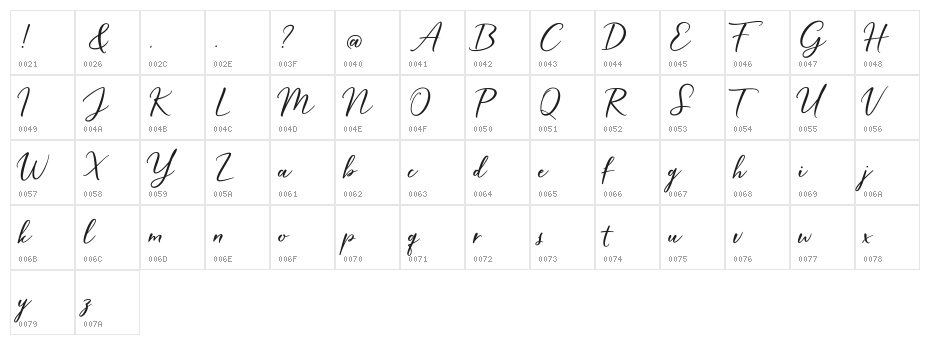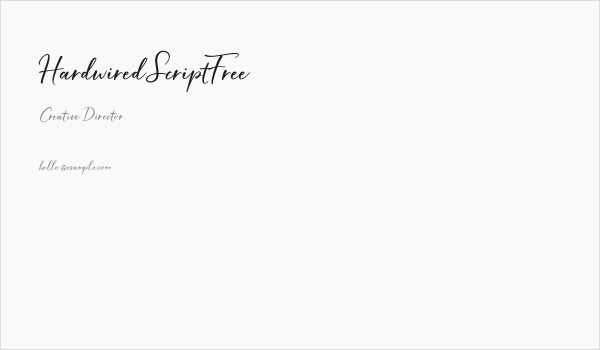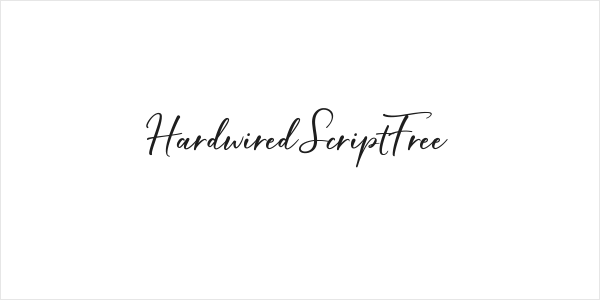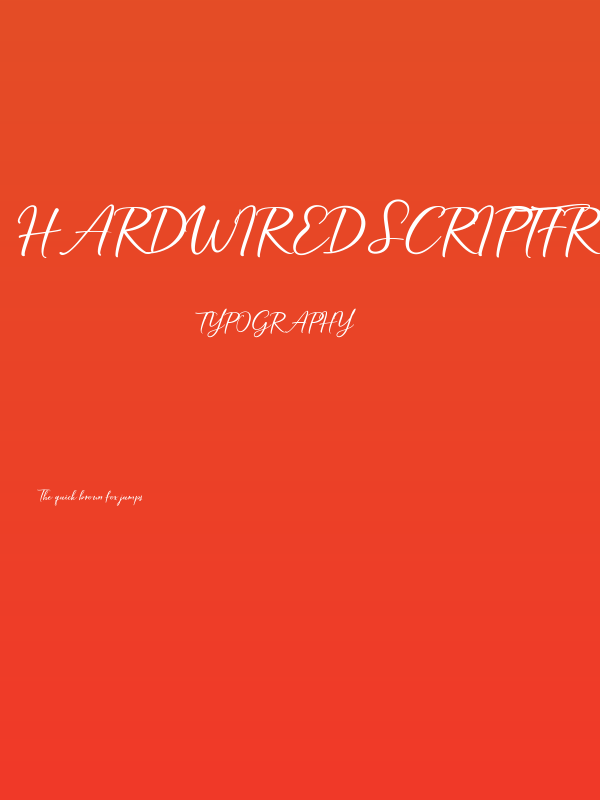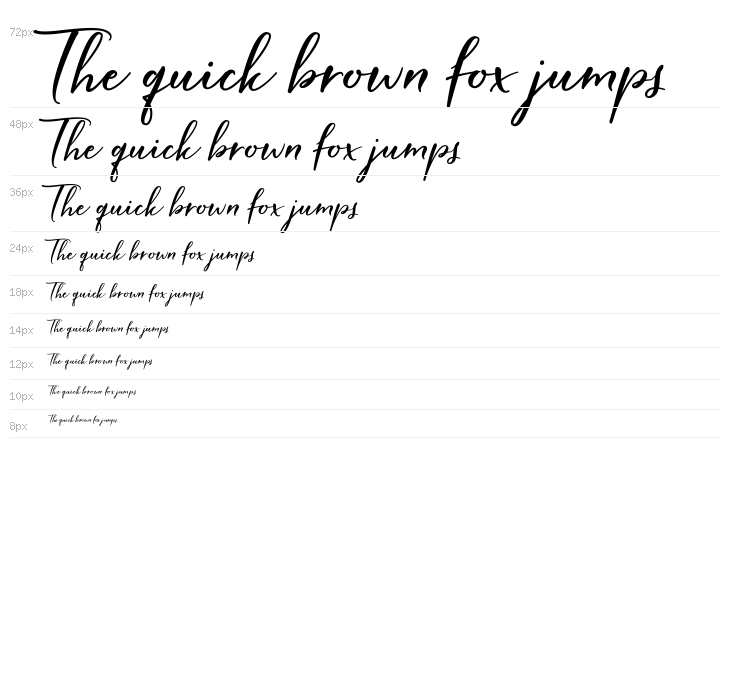
HardwiredScriptFree Font
| Gesamtstil | Elegant |
| Anwendungsfall | Logos, Invitations, Personal Stationery |
| Vorgeschlagene Projekte | Ideal for wedding invitations, elegant branding, personal stationery, and artistic projects requiring a touch of sophistication. |